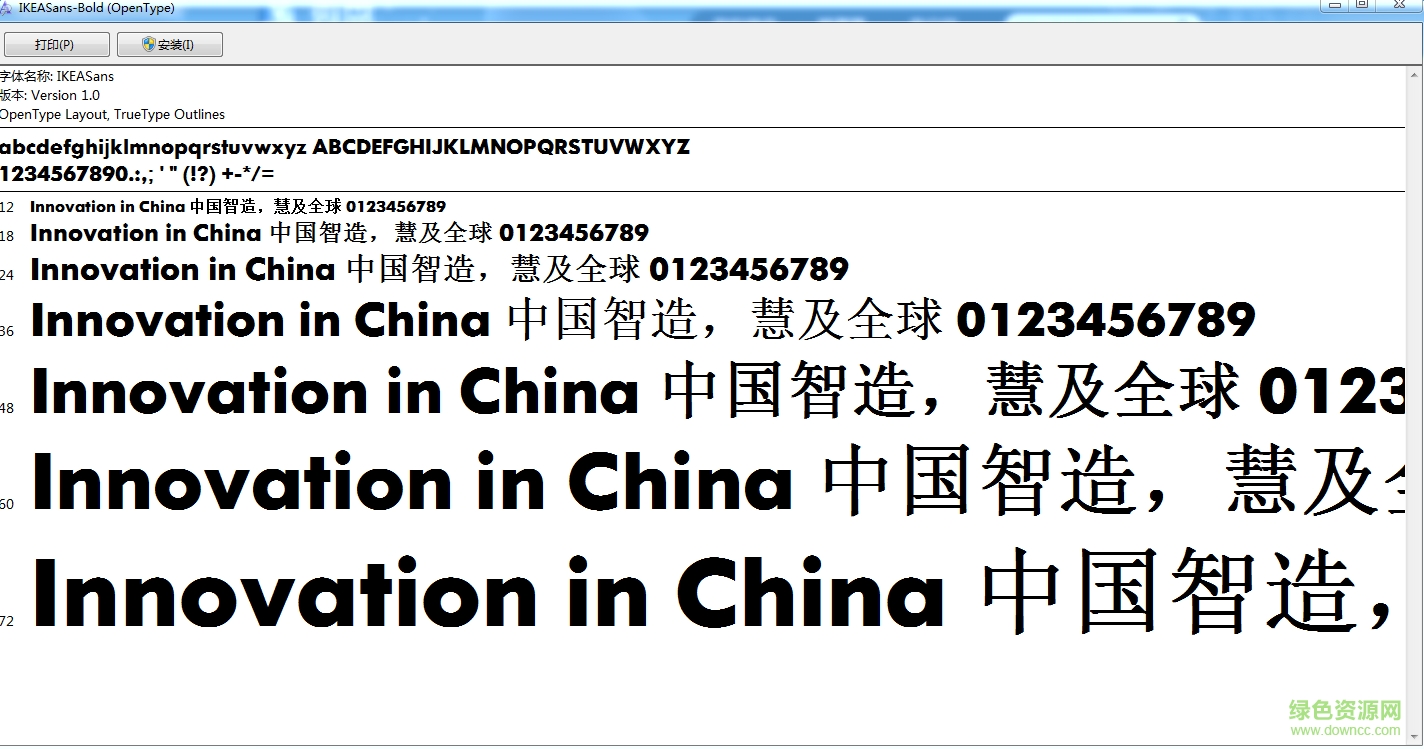
ikea sans bold字體是一款精美簡(jiǎn)潔的宜家商用字體,字型粗黑平整,線條流暢,筆劃粗重堅(jiān)實(shí),效果醒目,可用作標(biāo)題或宣傳標(biāo)語(yǔ),喜歡的朋友快來(lái)綠色資源網(wǎng)下載吧!
無(wú)襯線體介紹
無(wú)襯線體(Sans-serif)專指西文中沒(méi)有襯線的字體,與漢字字體中的黑體相對(duì)應(yīng)。與襯線字體相反,該類字體通常是機(jī)械的和統(tǒng)一線條的,它們往往擁有相同的曲率,筆直的線條,銳利的轉(zhuǎn)角。
幾何體無(wú)襯線體介紹
(Avant Garde、Century Gothic、Futura、Gotham)。顧名思義,幾何無(wú)襯線體是基于幾何形狀的,透過(guò)鮮明的直線和圓弧的對(duì)比來(lái)表達(dá)幾何圖形美感的一種無(wú)襯線字體